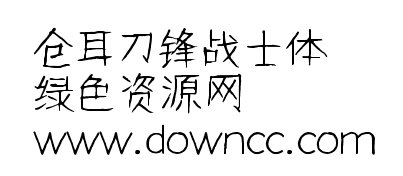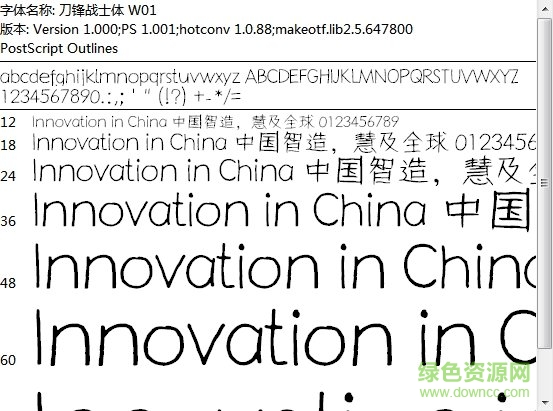
刀鋒戰(zhàn)士體是蒼耳字庫(kù)推出的一款卡通字體,每一個(gè)漢子都有著流暢舒緩的韻律,英文字母更是圓潤(rùn)活潑,讓文字變得輕松飛揚(yáng)起來(lái),給你悠閑安逸的閱讀體驗(yàn),綠色資源網(wǎng)誠(chéng)意推薦!
“月黑雁飛高,單于夜遁逃。欲將輕騎逐,大雪滿弓刀”,字體筆畫(huà)如同刀劈斧砍,果敢有力,一氣呵成。
蒼耳字庫(kù)最近推出的幾款字體,都十分出色,打破了以往字體的端正嚴(yán)肅之感,在系統(tǒng)字體中更有不同的韻味,給人大氣飄逸的體驗(yàn),可以廣泛使用在文字內(nèi)容相關(guān)的各個(gè)行業(yè)。